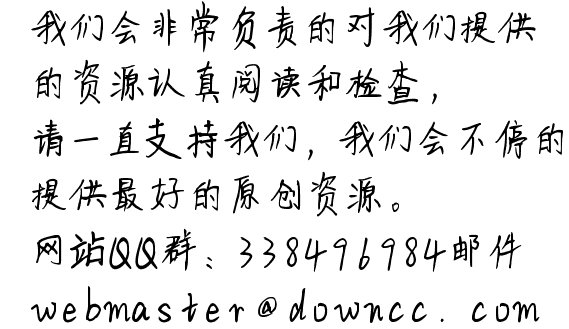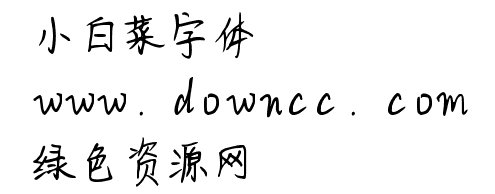
小白菜字體是一款筆觸細(xì)膩而纖長(zhǎng)的手寫字體,讓文字呈現(xiàn)出一股淡雅個(gè)性的韻味感,字庫(kù)完整,能滿足廣大用戶的生活工作需要,歡迎大家下載使用!
本字庫(kù)是在國(guó)家標(biāo)準(zhǔn)簡(jiǎn)體字庫(kù)GB2312所包含6763漢字的基礎(chǔ)上,又增加了近200常用字,已經(jīng)覆蓋了大陸99.75%的漢字使用頻率,足以滿足日常需求。